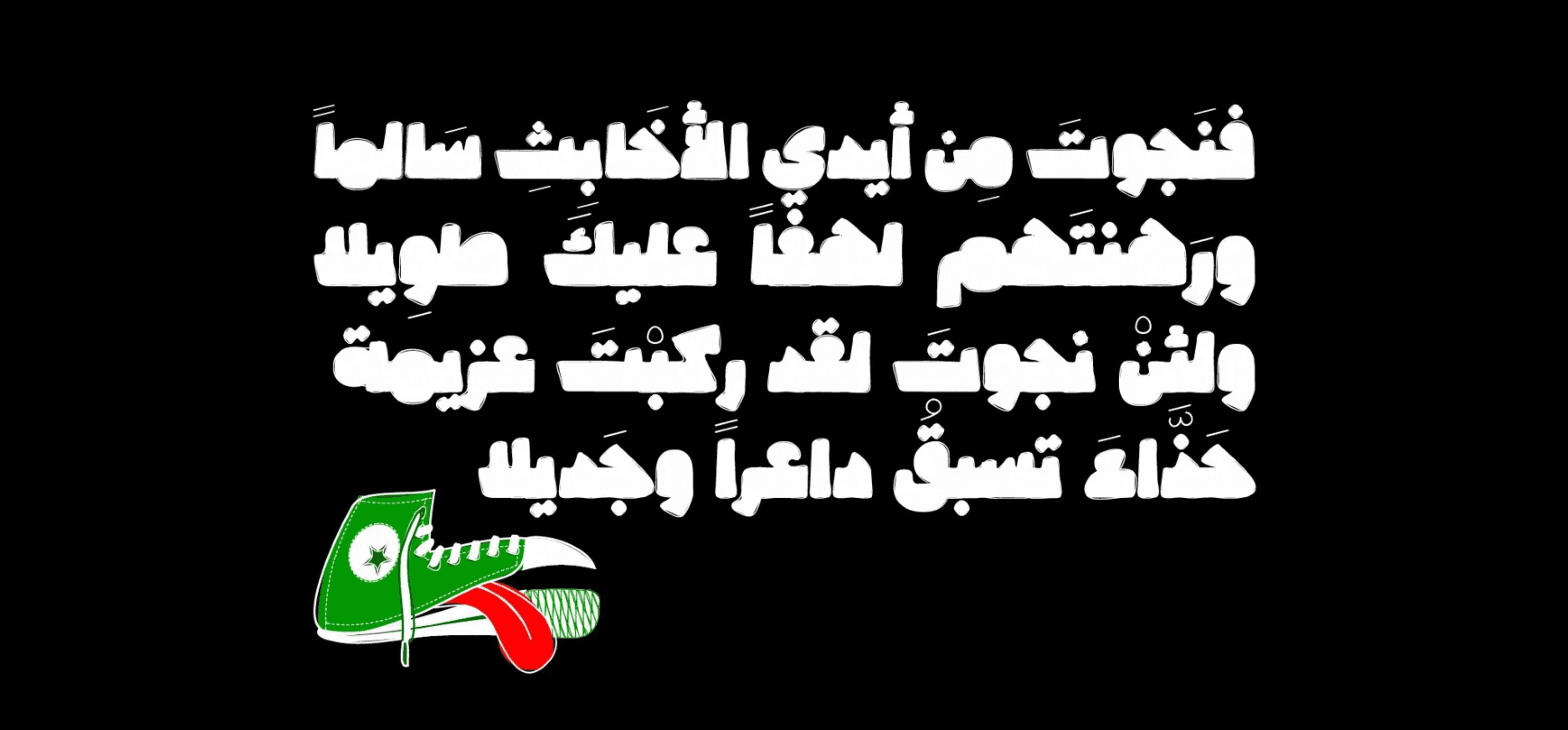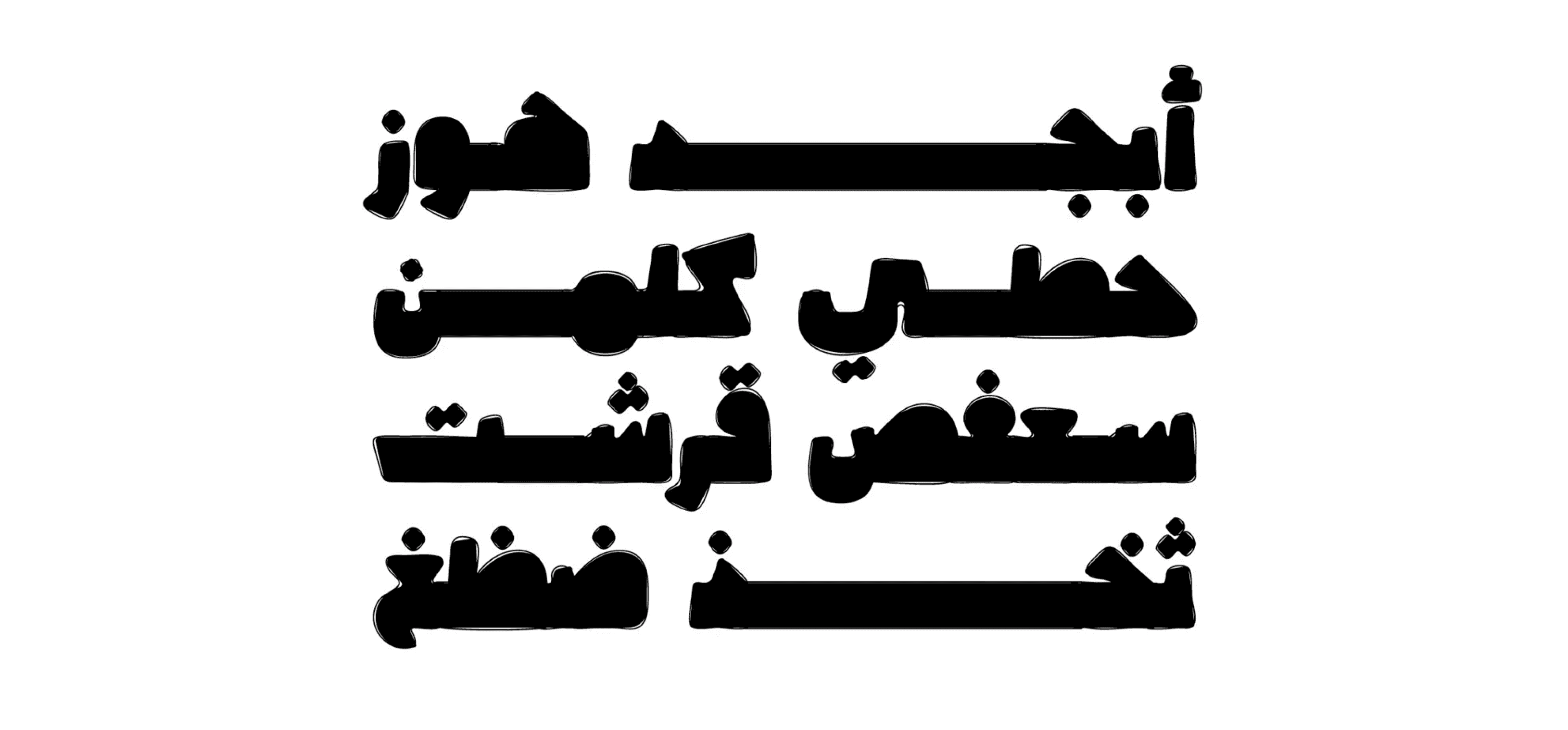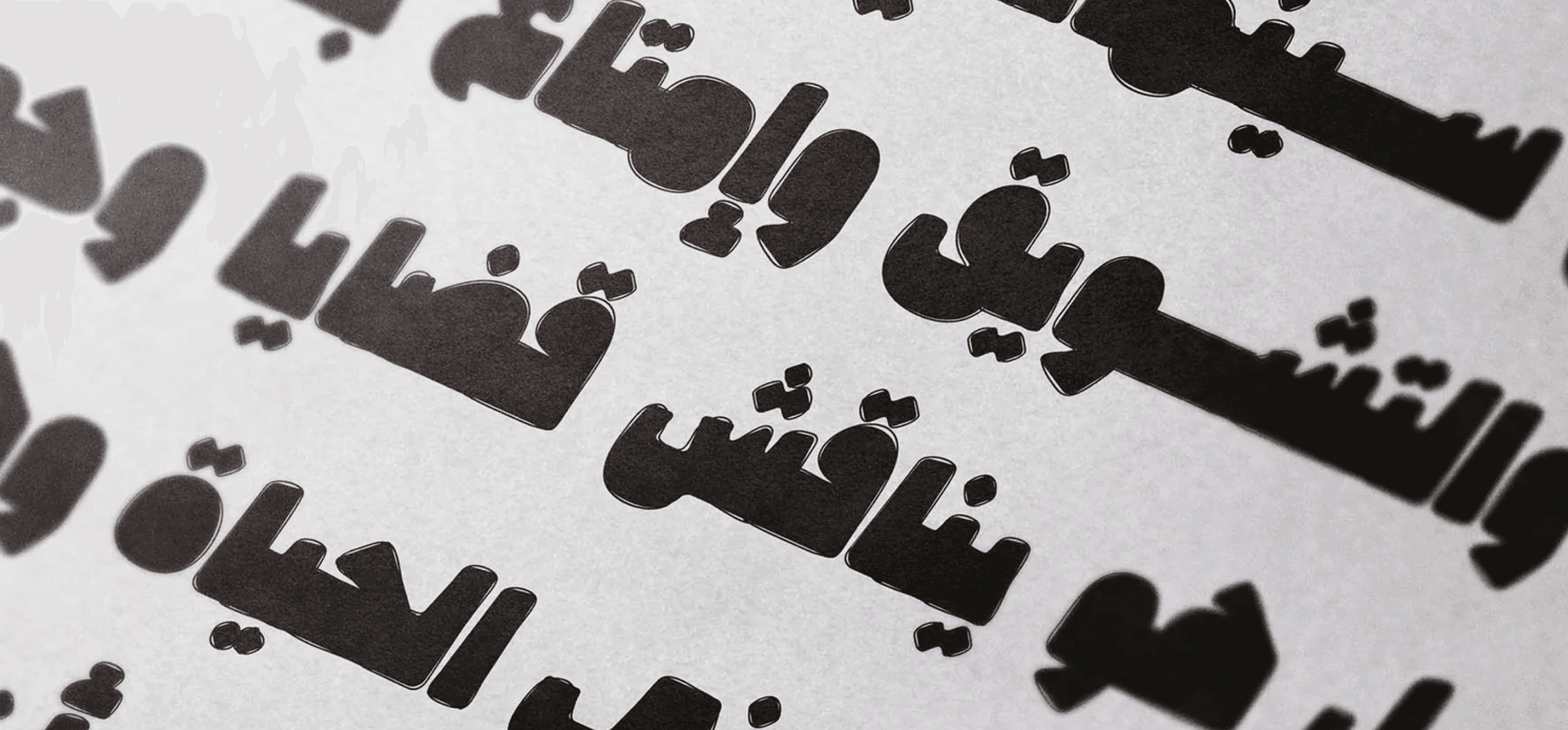
خط عربي مرح وملفت، يتميز بتصميم عريض وحروف غير تقليدية مستوحاة من أجواء الصيف والرسوم الكرتونية.
يعد مثاليًا لتصميم الشعارات، الإعلانات، التغليف، والمحتوى الترفيهي، خصوصًا الموجه للأطفال أو المشاريع ذات الطابع الطريف والبسيط.
كرووكي يمنح تصاميمك لمسة مرحة ومميزة، ويُعد خيارًا رائعًا لأعمال التصميم الإبداعية.